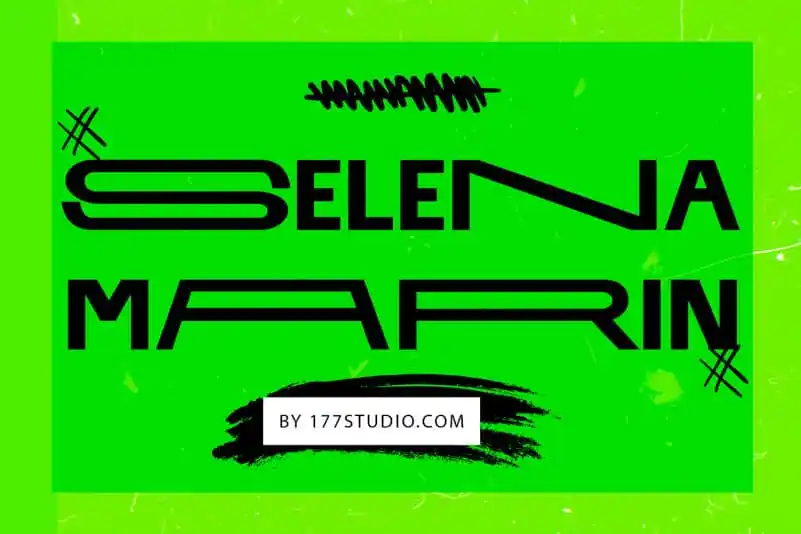
A “Selena Marin Font” é uma opção moderna para designers que buscam estilos limpos e sofisticados. Com largura variável e formas geométricas, ela evoca elementos de outros pop-sans serifados, mas incorpora modificações para um visual mais ousado e elegante. Ideal para aplicar em diferentes formatos gráficos, esta fonte é perfeita para criações como logomarcas, capas de revistas, interfaces web, títulos e cabeçalhos. Seu uso abrange uma ampla gama de aplicações, desde jogos até camisetas e outdoors. Com design moderno e sofisticado, a “Selena Marin Font” é um recurso indispensável para qualquer designer em busca de soluções de tipo originais.